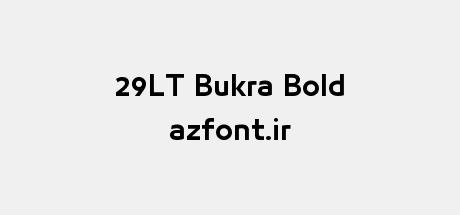
فونت زیبای رایگان 29LT Bukra Bold
قلم زیبای 29LT Bukra Bold از سری قلم های بسیار زیبا برای تایپوگرافی و لوگو تایپ می باشد.این قلم در وزن Bold و توسط Pascal Zoghbi & Khajag Apelian طراحی و منتشر شده است.